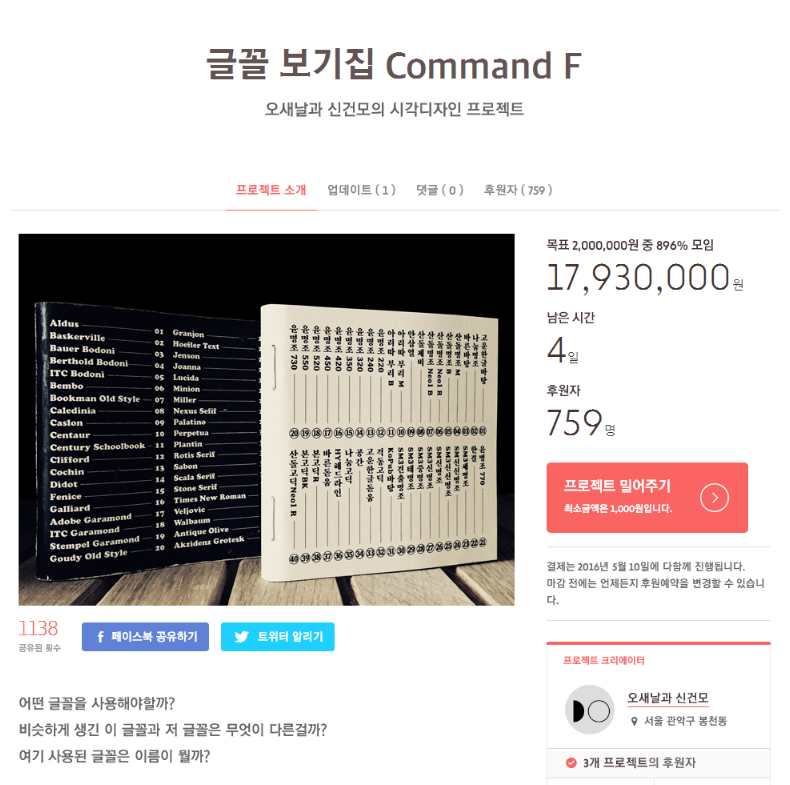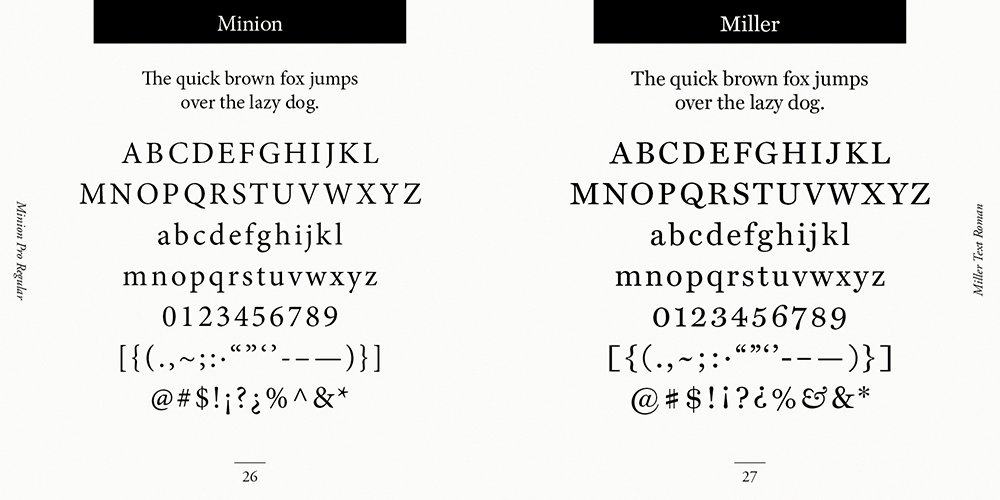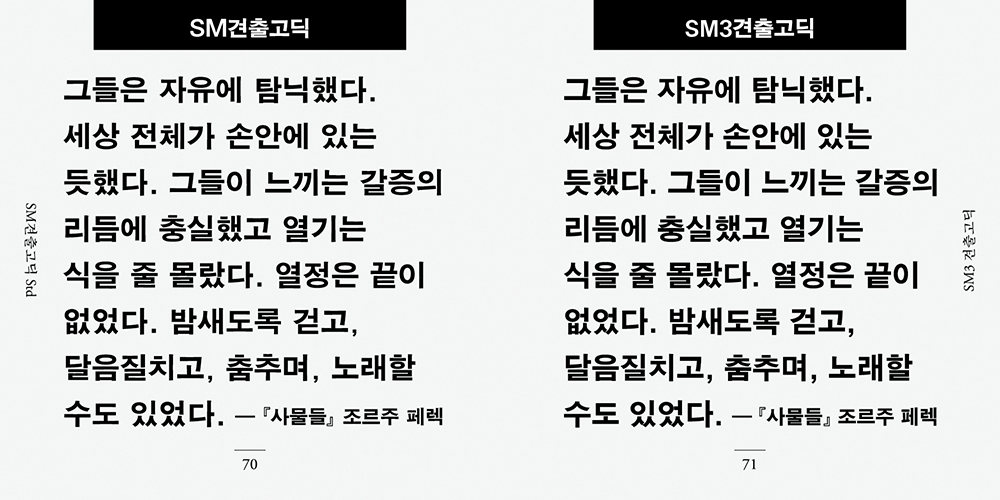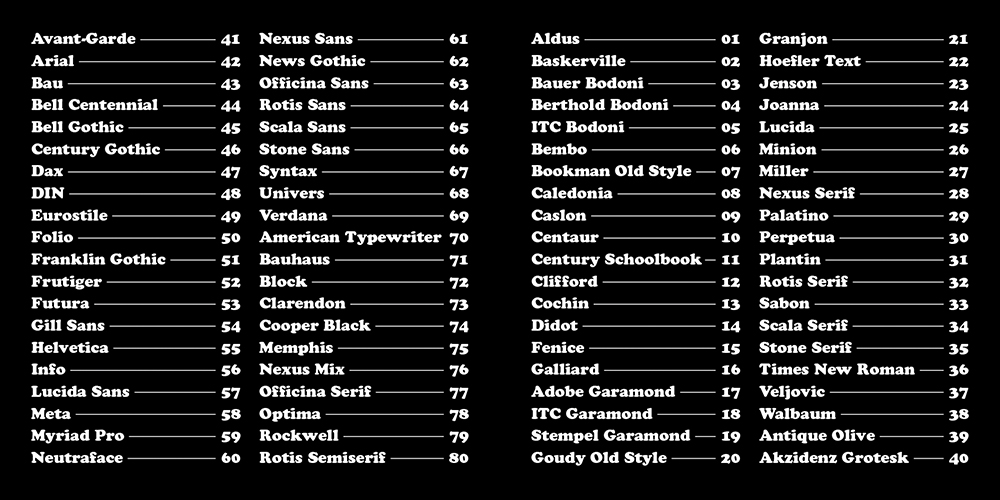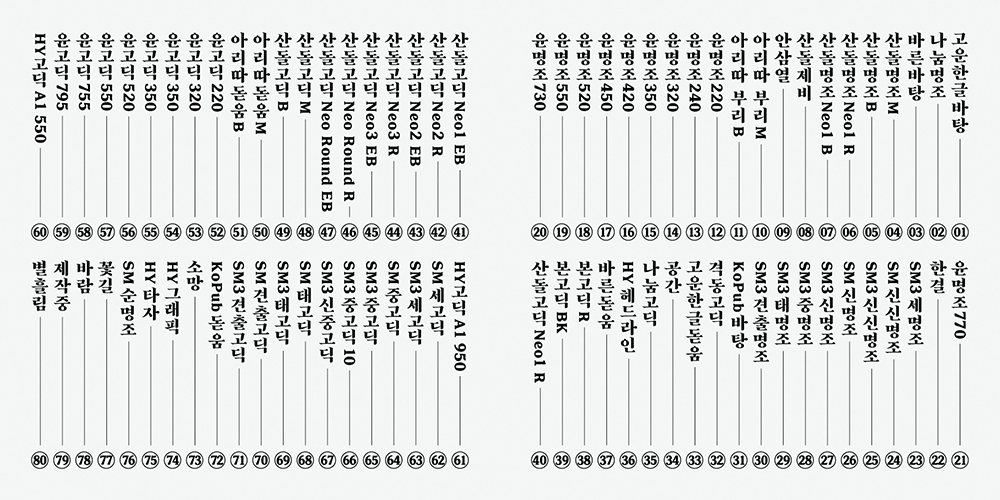
글꼴보기집 <커맨드 에프> : 제작자 오새날과 신건모
계원예술대학교에서 디자인을 공부한 오새날과 신건모는 글꼴보기집 <커맨드 에프(Command F)>를 제작했다. 크라우드 펀딩 플랫폼 텀블벅을 통해 더욱 질 좋은 책으로 제작되는 <커맨드 에프>는 어느덧 목표 금액의 700%를 초과 달성하며 모두의 기대를 돋우고 있다. 한 손에 쏙 들어오는 아담한 크기에 80개의 글꼴을 담기까지, 요모조모 관련 이야기를 들어보았다.
글꼴보기집 <커맨드 에프> : 제작자 오새날과 신건모
계원예술대학교에서 정보지식디자인을 공부했다. 타이포그래피 소모임인 텍스트(.txt)의 구성원으로 활동하던 2013년, 영문 글꼴에 관한 관심에서 <커맨드 에프(Command F)> 영문판을 만들었으며, 2015년 비슷한 취지에서 한글판을 제작했다. 현재 도서출판 마티에서 디자이너로 일하고 있다.
—
계원예술대학교에서 그래픽일러스트레이션을 공부했다. 오새날과 텍스트로 활동하며 함께 <커맨드 에프>를 만들었다. 현재 오경섭, 채희준과 함께 ‘낮인사’라는 이름으로 그래픽 디자인을 하고 있다.
<커맨드 에프> 소개를 부탁합니다.
오새날(이하 ‘오’): <커맨드 에프>는 글꼴보기집이에요. 영문판과 한글판 두 종류로 제작되었는데, 영문판을 먼저 만들었고 한글판은 2년 정도 지난 후에 만들기 시작했어요. ‘커맨드 에프’는 맥 OS 환경의 단축키로, 뜻은 ‘찾아보기’예요. 이 책의 목차이자 표지인 겉면을 보고 ‘이 번호대로 찾아서 봐라’ 이거죠. 그래픽 디자이너가 대부분 그렇듯 저희도 작업하면서 서체에 관한 고민을 많이 해요.
<커맨드 에프>는 어떤 서체가 좋은지에 대해 판단할 수 있도록 보여주는 소책자예요. 디자인을 하다 보면 직접 출력해서 비교해볼 일이 비일비재한데 그럴 때마다 뽑아서 볼 순 없잖아요. 그래서 저희가 대신 출력해서 묶었던 거죠. 질 좋은 종이에 좋은 상태로 뽑아두었으니 어떤 글꼴을 활용할지 참고하여 고민하면 좋겠다는 느낌으로 말이죠. 많이 쓰이고 또 잘 만들어졌다고 하는 서체들을 저희끼리 모으고, 서체 100개 리스트 같은 것들을 참고해서 목차를 구성했어요. <커맨드 에프>는 굉장히 단순한 책이에요. 아무 디테일도 없고, 단순히 서체가 몇 페이지에 위치하는지만 표지를 통해 설명하는 식이죠.
신건모(이하 ‘신’): 시각 디자인 작업을 하면서 디자인하는 것은 요리와 비슷하다는 생각을 종종 했어요. 요리에 채소나 고기 같은 재료가 필요하듯 디자인엔 텍스트나 이미지 같은 재료가 필요한 거죠. 그런데 우리가 음식을 먹을 때 반찬이 아무리 맛있어도 밥이 맛없으면 식사가 훌륭하다는 느낌이 잘 안 들잖아요.
시각 디자인에서도 역시 가장 기본이 되는 게 결국은 텍스트, 즉 글자들이더라고요. 그럼 타이포그래피는 밥 짓는 거랑 비슷하지 않나 하는 생각이 들었어요. 밥을 지을 땐 쌀을 고르는 게 가장 중요한 일이니 시각 디자이너는 글꼴을 잘 고르는 게 제일 중요하지 않겠냐고 생각한 거죠. 이걸 만든 저희도 글꼴에 대해서는 잘 몰라요. 보는 사람이 여러 종류의 쌀을 구경할 수 있도록 도와줄 뿐이에요.
저작권 문제가 어려웠을 것 같은데요. 텀블벅 페이지를 살펴보면 ‘활자공간의 폰트 라이선스’를 통해 지원받았다고 하는데, 관련 이야기를 들려주세요.
오: 서체가 샘플에 한정된 거라 해도 누군가는 이 서체들을 다 가지고 있어야 글꼴보기집을 만들어낼 수 있잖아요. 저희는 당시 학생이었고, 서체를 다 구매할 수도 없어서 고민하던 차에 대부분의 서체를 가지고 계신 이용제 선생님의 도움을 받게 되었어요. 여기에 지인들이 만든 자체 서체나 나눔고딕, 아리따 같은 무료 서체들을 포함해서 제작하게 되었죠.
신: 활자공간에서 서체 파일을 복사해준 게 아니라 아웃라인화 해주었어요. 이는 폰트의 기능을 없애고 이미지화해서 전달하는 방식인데, 서체 파일을 복사하는 것은 불법이지만 몇 글자를 이미지화하는 것까지는 서체 회사에서도 허락한 바라 이 방식을 활용해 제작하게 되었습니다.
표지에 관해 이야기해보고 싶습니다. 제목보다는 목차를 눈에 띄게 구성한 점, 한글판 표지는 세로쓰기인 한편 영문판에서는 가로쓰기로 구성한 점 등이 눈에 띄는데요.
오: 영문판을 디자인할 당시 제가 쿠퍼 블랙(Cooper Black)에 빠져있었어요. 통통하고 귀여운 모양이 좋아서 그걸로 하자고 했죠.
신: 영어는 가로쓰기가 기본이라 당연하게 가로로 디자인했어요. 그 이후에 한글판을 제작하면서 이 둘이 형제처럼 보였으면 좋겠다 싶어서 ‘바람체’를 골랐어요. 통통하고 볼륨감 있는 게 비슷한 느낌이어서요. 바람체가 원래 세로쓰기 서체니까 제작 의도를 살리고자 했죠.
영문판은 세리프에서 산세리프 순서로, 한글판은 명조체에서 고딕체 순서로 하여 각 ABC, 가나다순으로 정렬한 것 같은데요. 뒤쪽으로 갈수록 목차가 그 구분에서 모호해지는 것 같아요.
신: 글꼴이 먼저 생기고, 분류는 누군가 나중에 하는 거잖아요. 그것처럼 저희도 이 글꼴들을 정리하다 보니 영문판엔 세리프와 산세리프, 한글판엔 명조와 고딕이라는 구분이 생겼고, 이 모두에 포함되지 않는 글꼴들이 남았죠. 이분법에 맞추어 안 맞는 서체를 빼는 건 아쉬워서 세리프/산세리프, 명조/고딕 그리고 기타 글꼴을 수록한 거죠.
그런데 실은, 영어는 철저하게 ABC 순서를 따르고 있지만 한글판은 벗어난 글꼴들도 있어요. 이를테면 나눔고딕 다음에 바른돋움이 바로 나와야 매끄러운데 HY헤드라인이 등장하는 식이죠. 이런 식으로 배치한 이유는 가나다순보다 좌우에 배치되는 서체를 우선했기 때문이에요. 같은 서체인데 레귤러와 엑스트라볼드가 앞뒷면에 오면 비교하기가 어렵잖아요. 이런 경우를 막기 위해 중간중간 가나다순을 어기면서 다른 서체를 삽입한 거죠.
이탤릭, 볼드, 컨덴스드, 익스텐디드 등을 지원하는 서체의 경우 패밀리 전체를 소개하고 싶은 욕심도 있었을 것 같은데요.
신: 패밀리 전체를 보여주면 그 회사의 서체 샘플북을 만든 거나 다름없을 거로 생각했어요. 그래서 기본형 서체만 보여주고자 한 거죠. 그런데 한글판의 경우에는 굵기에 차이를 두어 실은 서체들도 있어요. 예컨대 윤명조 730, 770 같은 게 그렇죠. 거기에 더해서 이런 이유도 있었어요. 우리는 한글을 훨씬 많이 사용하잖아요. 그래서인지 영어보다는 굵기가 다른 종류의 서체를 사용할 기회가 더 많아요. 그러다 보니 굵기가 다른 샘플도 필요하단 생각이 들었어요.
<커맨드 에프>에서 개인적으로 선호하는 글꼴이 있다면 꼽아주세요.
신: 영문판 40번에 있는 악치덴츠 그로테스크(Akzidenz Grotesk)와 한글판 71번의 SM3 견출고딕이요. 저에게 타이포그래피 관련하여 지대한 영향을 주신 분이 워크룸의 김형진 선생님이신데 그분이 추천해주신 것들이에요. 둘 다 좀 투박하지만, 글자의 원형을 가장 잘 담고 있는 서체라고 생각해요.
오: 저는 영문판 78번의 옵티마(Optima)와 한글판 74번의 HY 그래픽이요. 사실 저는 옵티마의 매력을 잘 몰랐는데, 타이포그래피 소모임 활동을 통해 그 매력을 알게 되었어요. 당시 건모 씨가 옵티마와 어울리는 글꼴로 HY 그래픽을 추천했는데 그 둘이 섞인 걸 보고 완전히 마음을 빼앗겼죠.
이번 프로젝트를 진행하며 서체나 타이포그래피에 관해 새롭게 배운 바가 있다면 들려주세요.
신: 영문이나 한글이나 마찬가지인데요, 이름이나 주요 특징을 텍스트로만 인지하고 있던 글꼴들이 있었어요. <커맨드 에프>는 그런 글꼴들을 직접 확인하고 공부할 수 있던 기회였지요. 머릿속으로만 생각했던 것과 실제 모양에 차이가 있어 괴리감을 느끼는 글꼴도 있었어요. 또, 잘 알고 있던 글꼴도 이게 이렇게 생겼었나? 하고 문득 낯설어하기도 했고요.